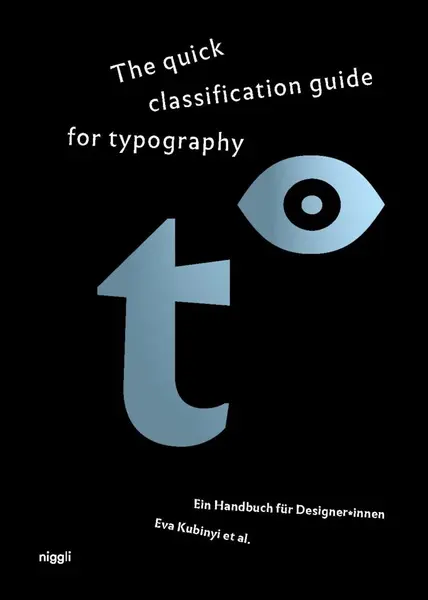
Mit »The quick classification guide for typography« erschien im Niggli-Verlag ein Buch zum Thema Schriftklassifikation. Erhältlich ist das Buch in deutscher oder englischer Sprache mit gleichem Titel. Die deutsche Version ist an dem Untertitel »Ein Handbuch für Designer:innen« erkennbar. Das Buch basiert auf einem Forschungsprojekt, dessen erster Meilenstein die Typ-o-App (www.typ-o.eu) war. Die App, analoge Spiele und schließlich das Buch verfolgen gemeinsam das Ziel, die Vielfalt an Schriften verständlich zu strukturieren und die Fähigkeit zur differenzierten Wahl und Anwendung von Schrift zu fördern.
Anlass für das Projekt war ursprünglich eine Typo-Safari, bei der Studierende Schriften im Stadtraum fotografierten und mithilfe automatischer Erkennungssoftware bestimmen sollten. Das klappte jedoch nur bedingt. Mit der App sollte daher ein interaktives Bestimmungstool entwickelt werden, bei dem man sich nicht nur auf Algorithmen stützt, sondern auf einen klar strukturierten Lernprozess. Inspirationsquelle waren klassische Pilzbestimmungsbücher mit stufenweiser Bestimmung, erklärt Prof. Eva Kubinyi.
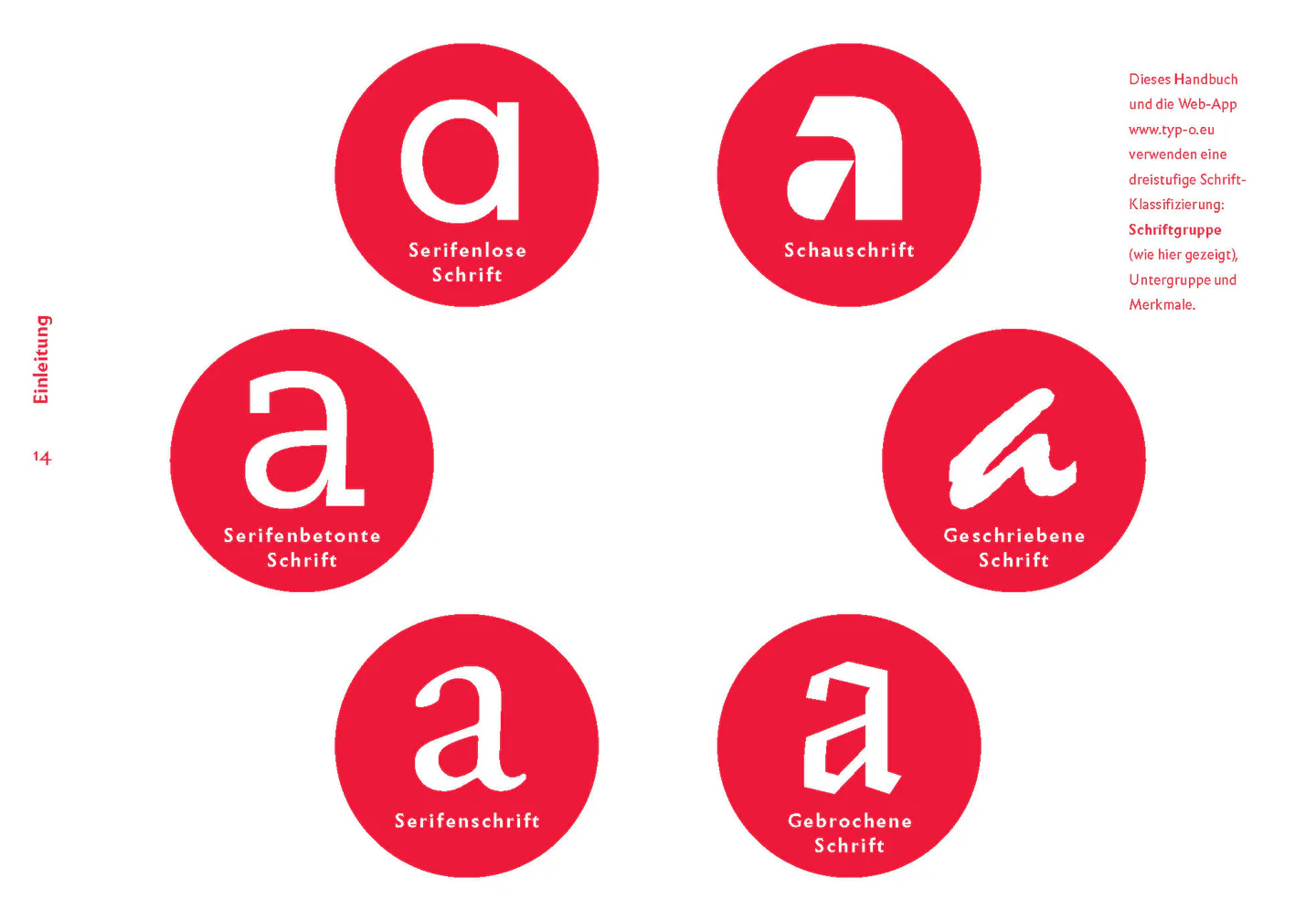
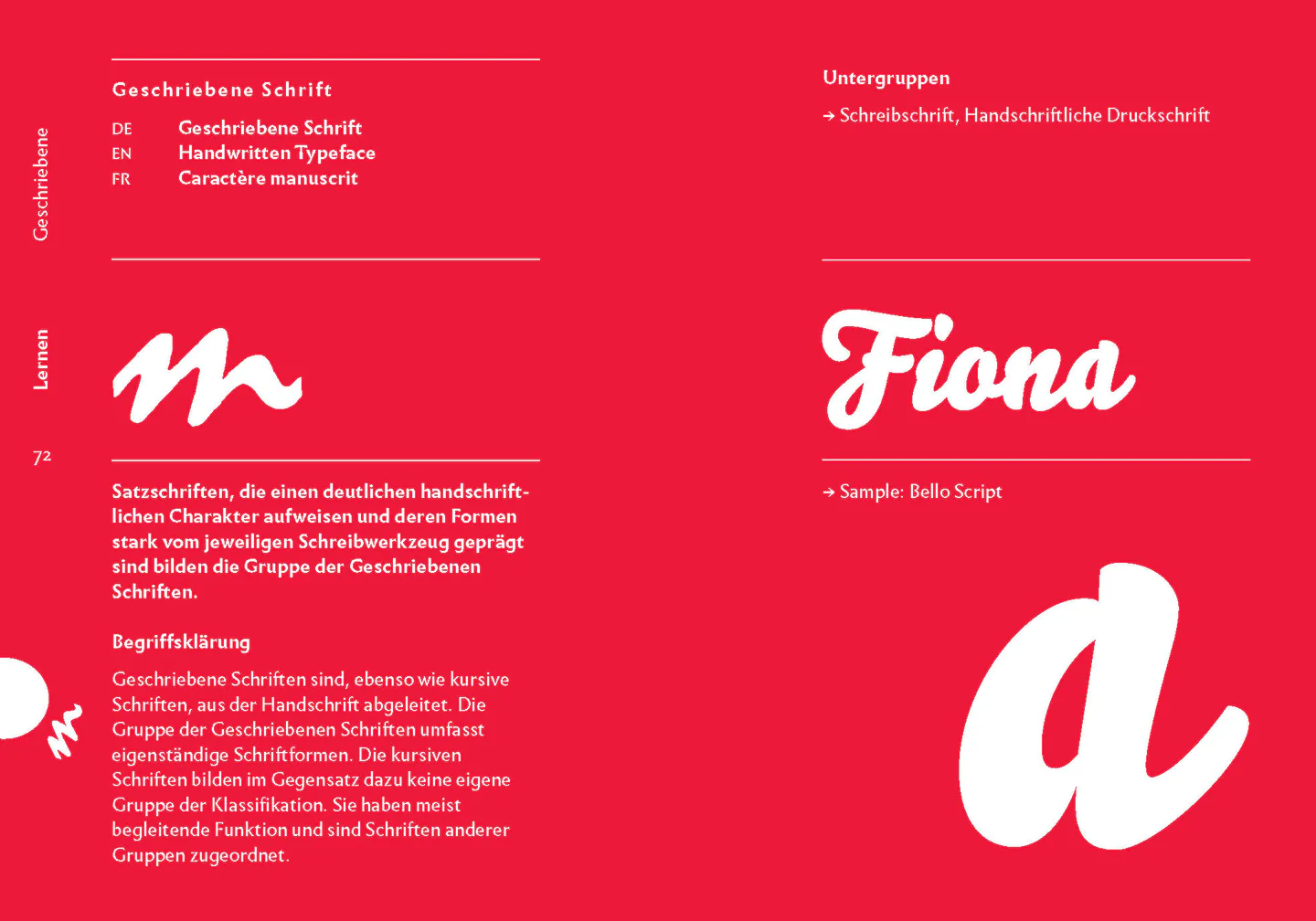
Die Umsetzung des Projektes als Buch beginnt mit einer ausführlichen Einleitung zum Thema Schriftklassifikation über knapp 90 der 400 Seiten des Buches. Die üblichen, älteren Klassifikationssysteme (nach Vox, DIN usw.) werden dabei wegen ihrer mangelnden Praxistauglichkeit nur gestreift und es wird vielmehr ein eigenes System propagiert, dass Schriften zunächst grob in sechs Hauptgruppen einteilt, die dann noch einmal in passende Untergruppen (wie dynamisch/statisch/geometrisch) untergliedert werden.
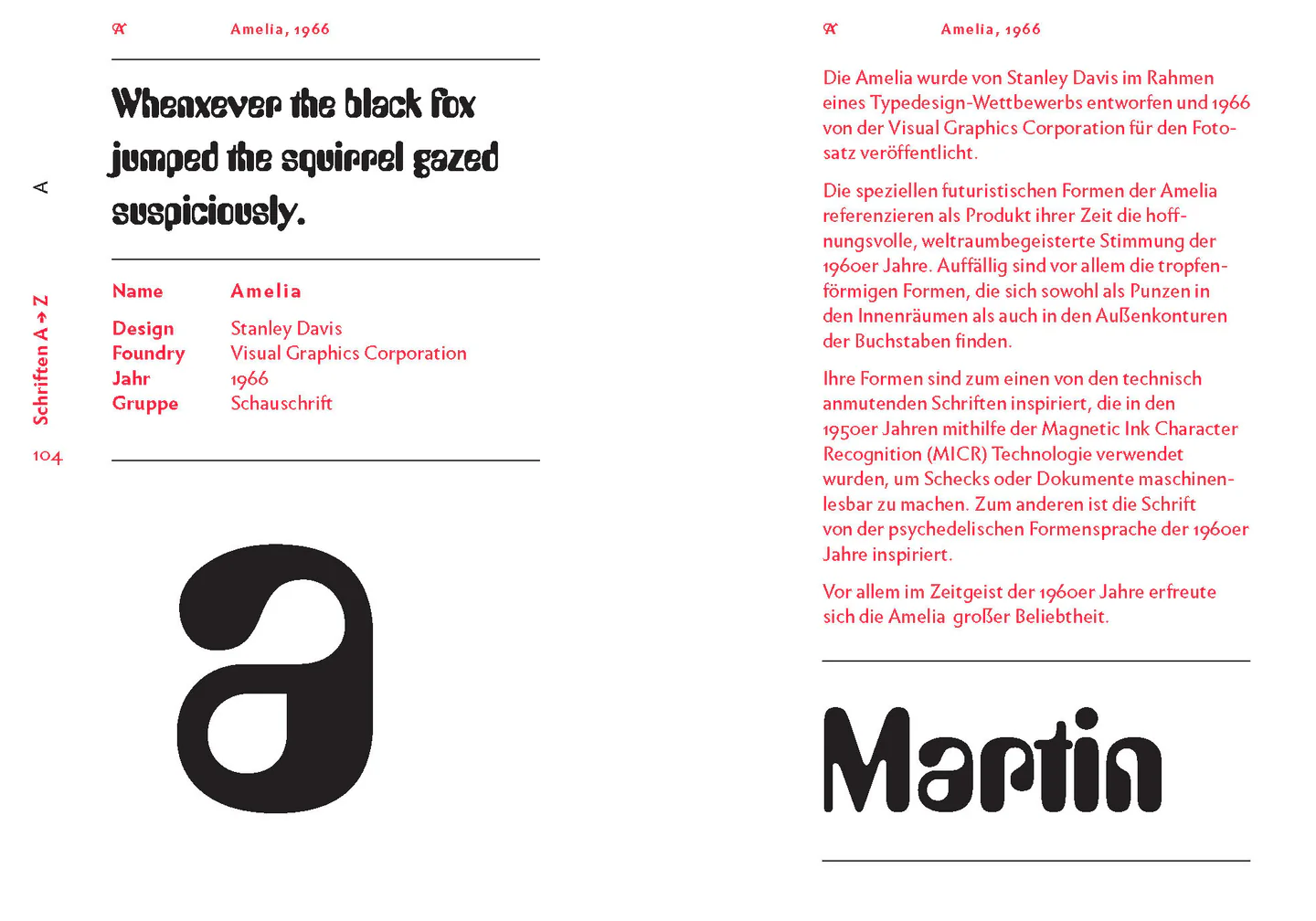
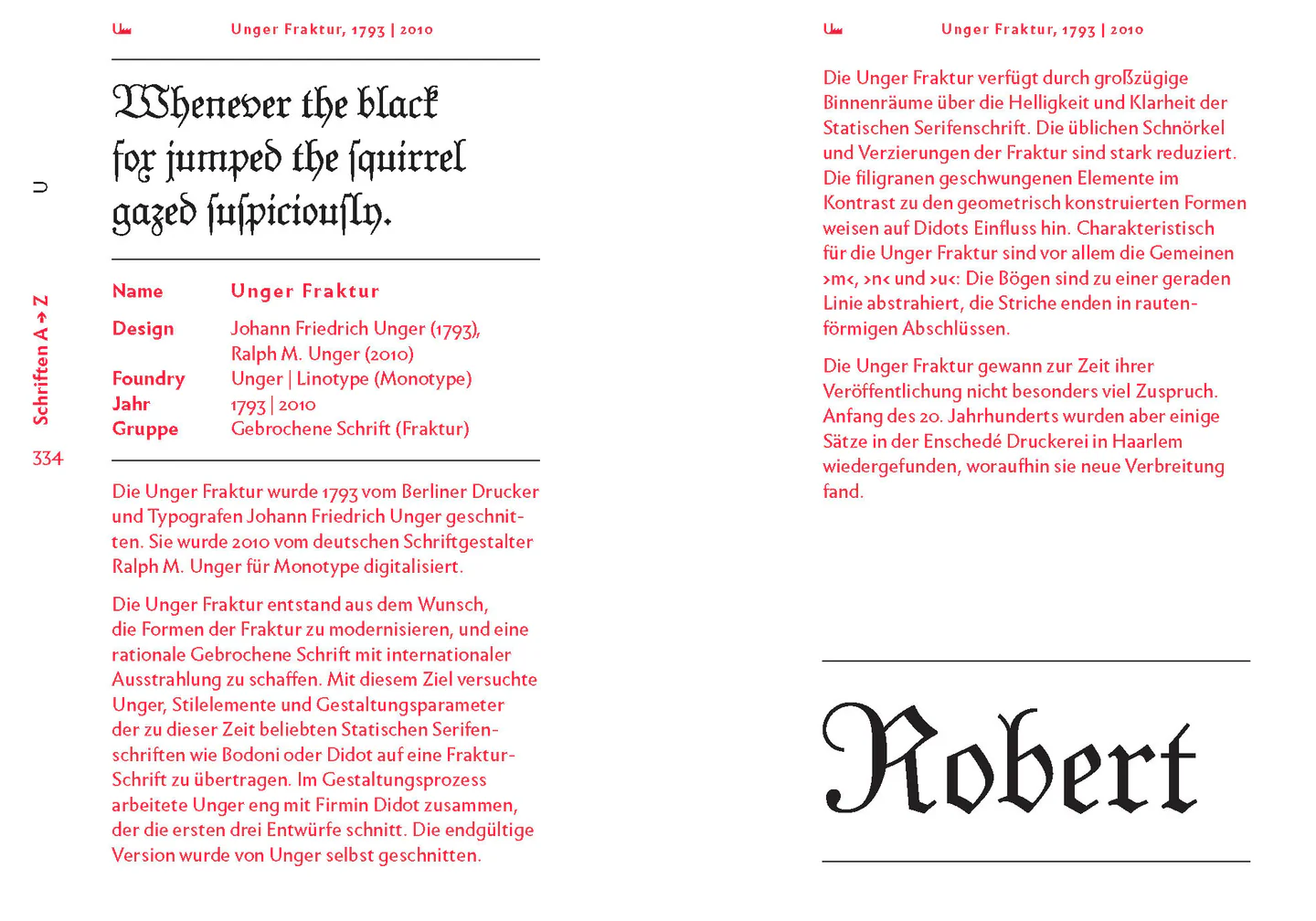
Den größten Teil des Buches machen dann circa 100 Schriftvorstellungen aus, die den entsprechenden Klassifikationsgruppen zugeordnet sind. Die Auswahl, die als Mischung »relevanter, prototypischer Schriften« beschrieben wird, enthält Klassiker des 20. Jahrhunderts genauso wie Schriften der letzten 20 Jahre.
Abgerundet wird das Buch durch ein Glossar für zugehörige Fachbegriffe.
Fazit
Der größte Mehrwert steckt für mich vor allem in den ersten 90 Seiten, die Design-Studenten und schriftbegeisterten Quereinsteigern (die typografische Fachbegriffe nicht scheuen) ein praxistaugliches Klassifikationssystem näherbringen. Die Schriftvorstellungen selbst können bei heute zehntausenden verfügbaren Schriften naturgemäß nur eine willkürliche Auswahl sein. Positiv hervorzuheben ist dabei aber, dass zu allen Schriften nützliche Hintergrundinformationen geliefert werden. Diese sind übrigens auch über die Projektwebsite weiterhin kostenlos verfügbar. Man müsste für sie das Buch nicht zwingend erwerben. Dennoch hat natürlich auch das lineare Durchlesen ein gedruckten Buches fernab von Bildschirmen weiterhin seine Berechtigung und mit einem Preis von 35 Euro kann man bei diesem Buch nicht viel falsch machen.
Untertitel: Ein Handbuch für Designer:innen